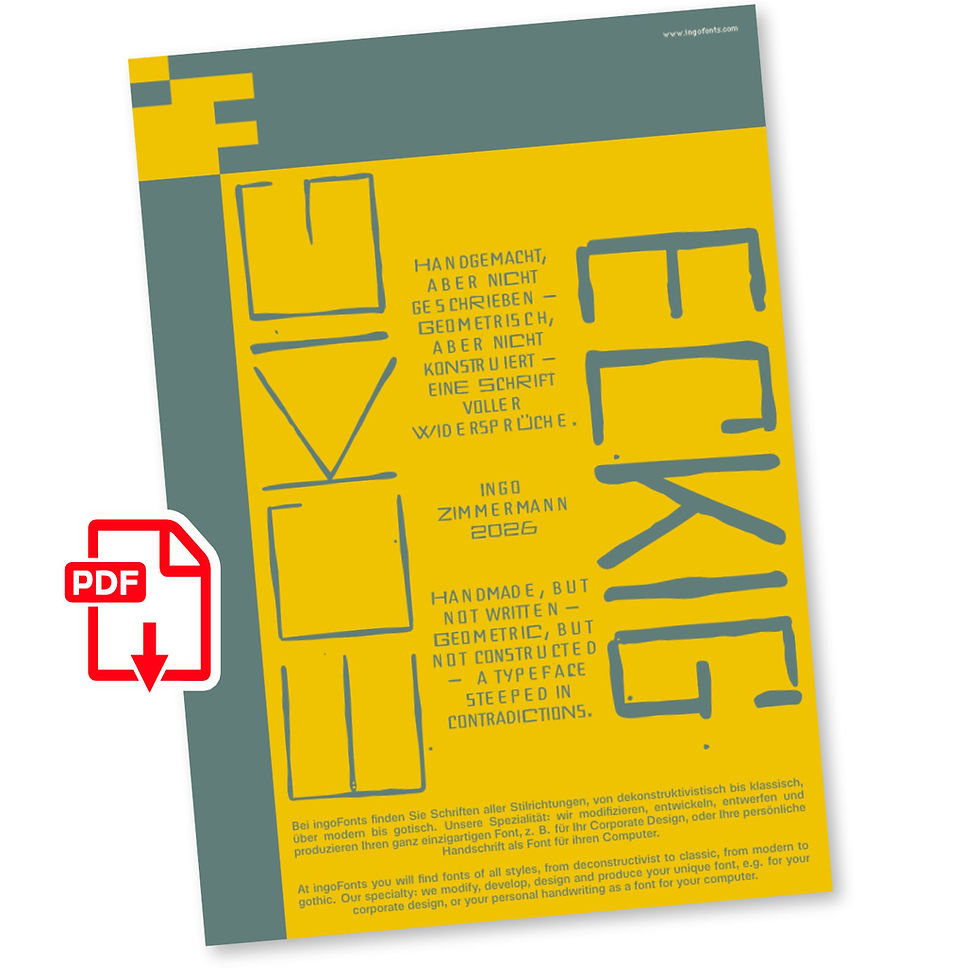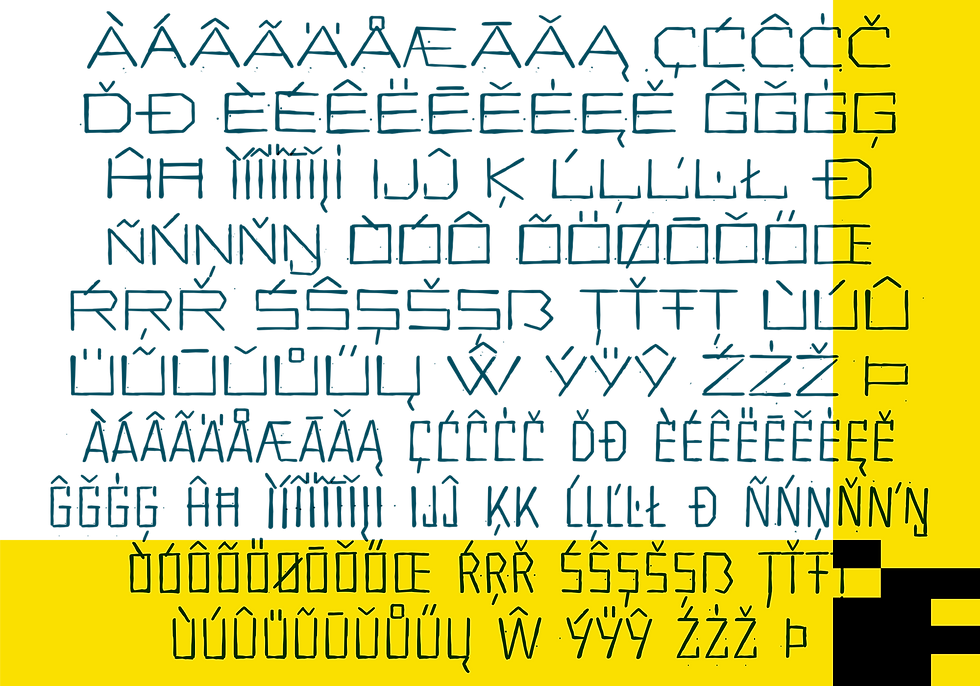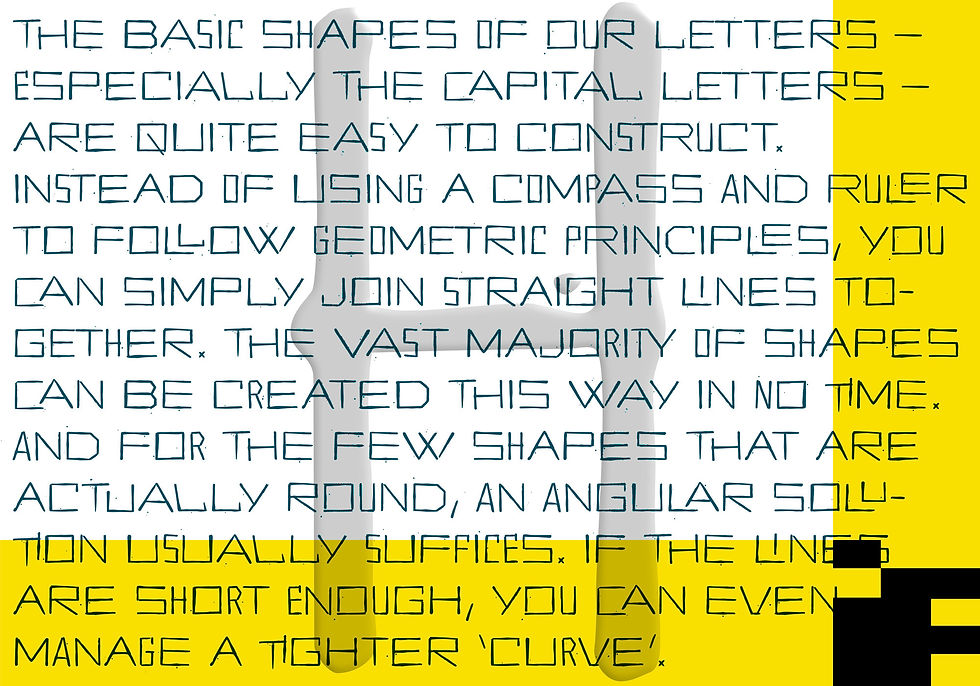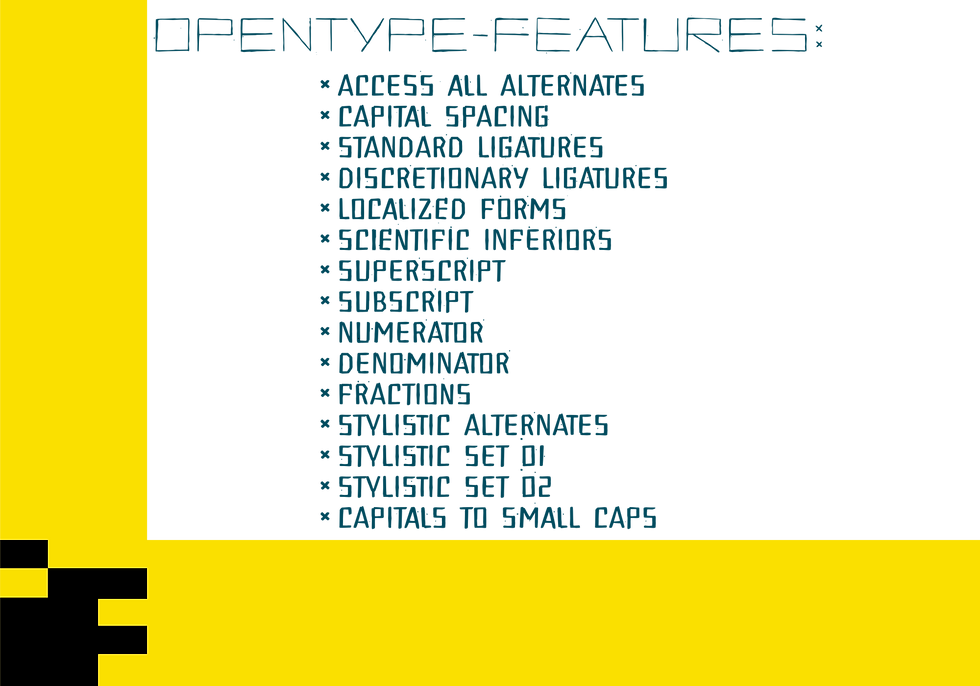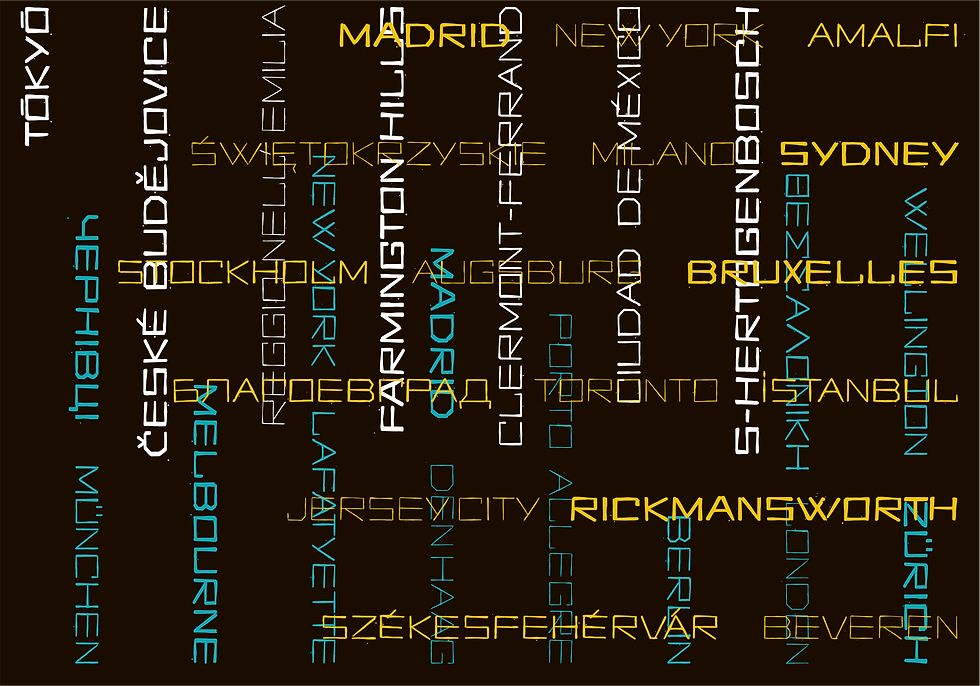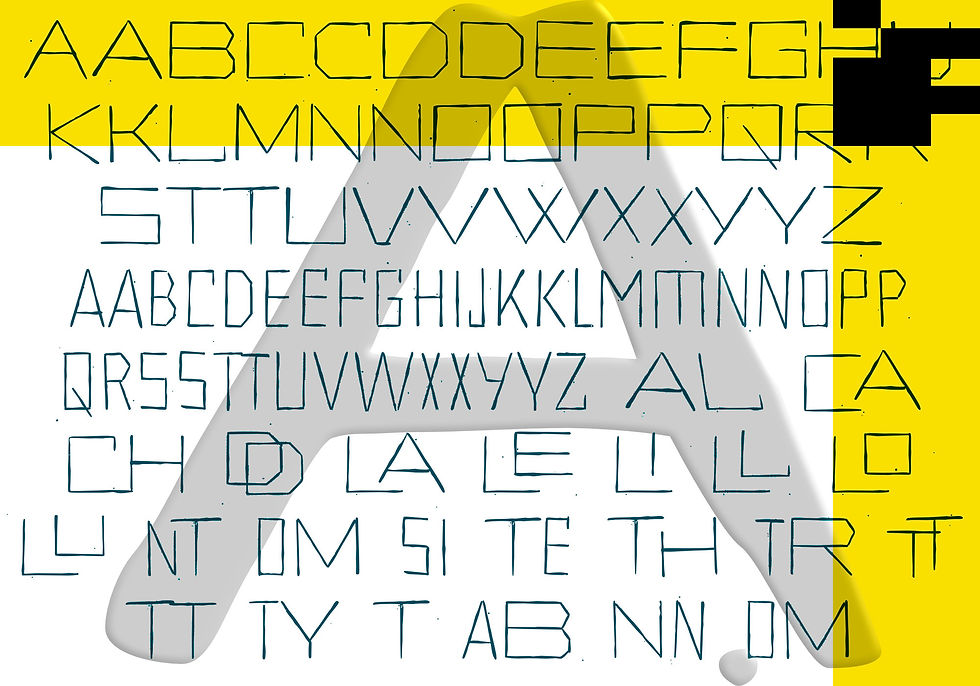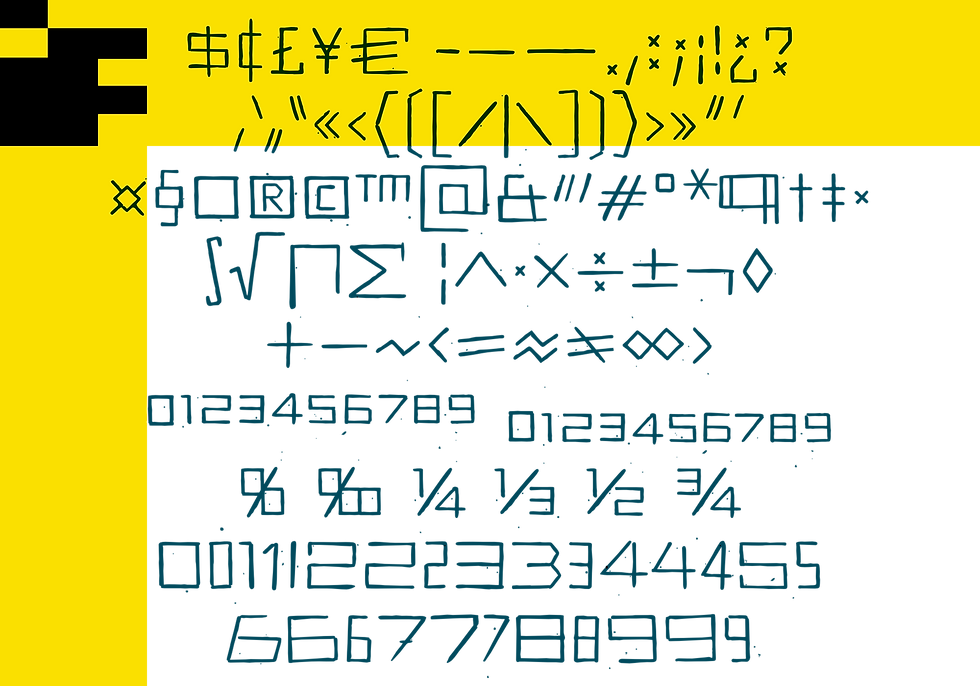
Handgemacht, aber nicht geschrieben – geometrisch, aber nicht konstruiert – eine Schrift voller Widersprüche.
Die Grundformen unserer Buchstaben – vor allem die Grossbuchstaben (Versalien) – lassen sich recht einfach konstruieren. statt mit Zirkel und Lineal nach geometrischen Prinzipien vorzugehen, kann man auch ganz simpel gerade Striche aneinanderfügen. Die allermeisten Formen sind so schnell angelegt. Und für die wenigen eigentlich runden Formen tut es meist auch eine eckige Lösung. Sind die Striche nur kurz genug, dann gelingt auch mal eine engere „Kurve“.
Die ECKIG ist so eine reine Versalschrift – die Kleinbuchstaben sind mit einer schmalen Form der Grossbuchstaben belegt. Die Vorlage für die Schrift enstand in einer Art von Druckverfahren. Als Stempel dienten die Kanten von mehreren Metallplatten. Die verwendete Acrylfarbe war für diesen Zweck eigentlich zu flüssig. Aber den daraus resultierenden „handgemachten“ Charakter einschliesslich der kleinen danebengegangenen Farbspritzer wollte ich im fertigen Font unbedingt erhalten. So kommt es dass diese eigentlich streng eckig konzipierte Schrift eine weiche und flüssige Anmutung ausstrahlt.
Das Schöne an Handgemachtem ist ja, dass vermeintlich Gleiches eben nicht genau gleich ausgeführt ist. Da ist zum einen der Unterschied zwischen den annähernd quadratisch gehaltenen Grossbuchstaben und den deutlich schmaleren Kleinbuchstaben. Von den allermeisten Buchstaben der ECKIG gibt es auch mehr oder weniger unterschiedlich gestaltete Alternativformen.Mit Hilfe der OpenType-Features „Ligaturen“, „Seltene Ligaturen“, „Alternative Formen“, und „Grossbuchstaben als Kapitälchen“ sind diese individuell gezielt auswählbar.
So kann man beim Spiel mit den entsprechenden Optionen mindestens drei sehr unterschiedliche Anmutungen erzielen:
1) Nur Grossbuchstaben: wenn man nur die „Grossbuchstaben“ verwendet ist die Schrift sehr breit und monumental.
2) Nur Kleinbuchstaben: mit der Funktion c2sc „Grossbuchstaben als Kapitälchen“ werden alle Buchstaben in die schmalen „Kleinbuchstaben“ umgewandelt.
3) Die „wilde Mischung“: bei aktivierten „Ligaturen“ und noch mehr bei aktivierten „Seltenen Ligaturen“ werden alternative Buchstabenformen eingesetzt und breite und schmale Formen wechseln sich ab, so dass im Schriftbild maximale Abwechslung entsteht.